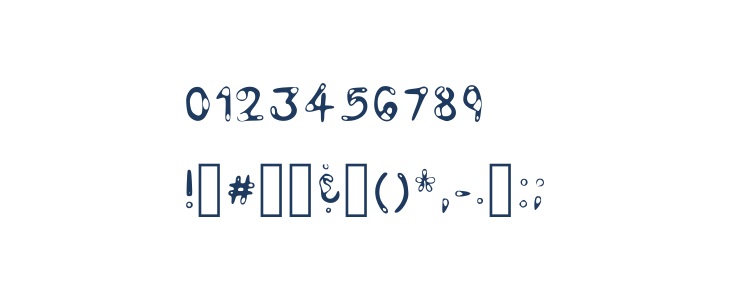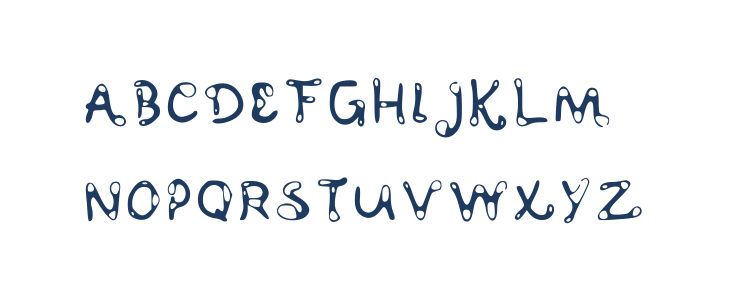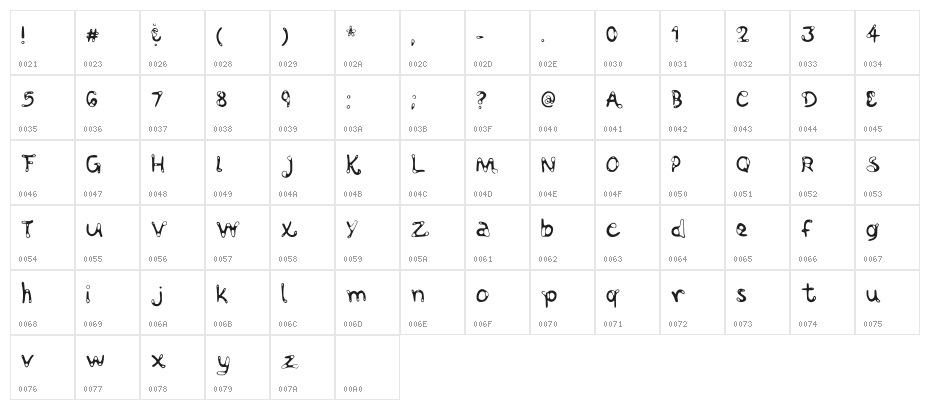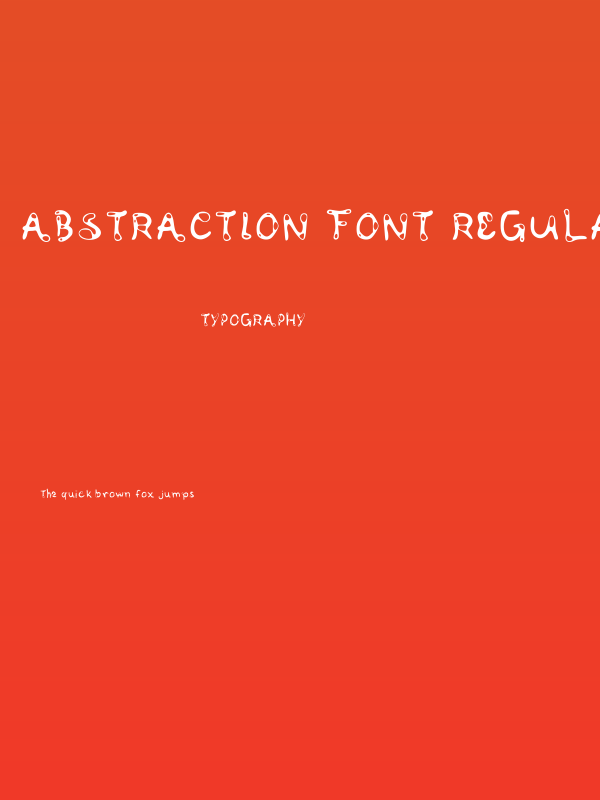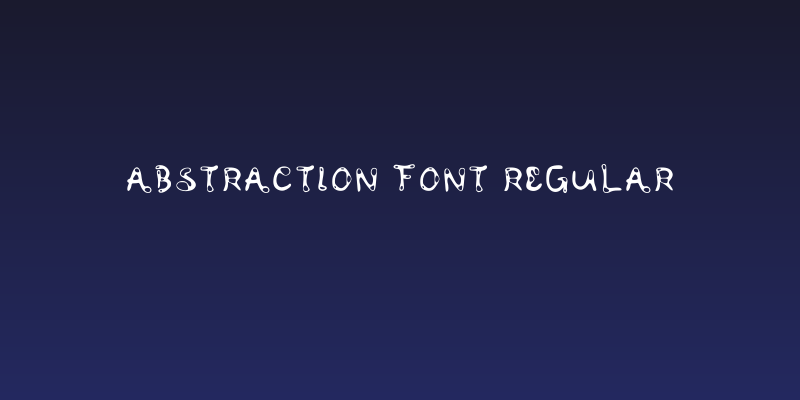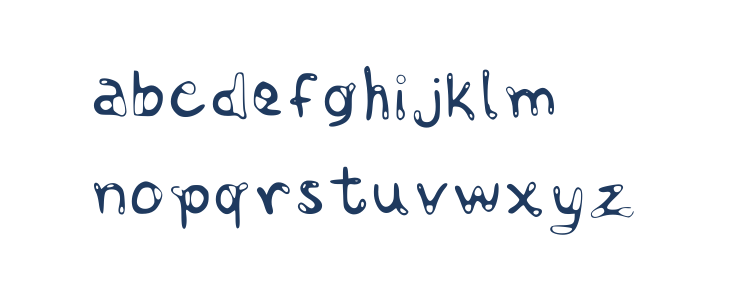
Abstraction Font Regular Font
✎ bubble letter
| Categorie | bubble letter |
| Stile generale | Decorative, Artistic, Playful |
| Caso d'uso | Logos, Headlines, Posters, Invitations |
| Progetti proposti | Children’s books, creative posters, party invitations, branding for playful products, art projects. |